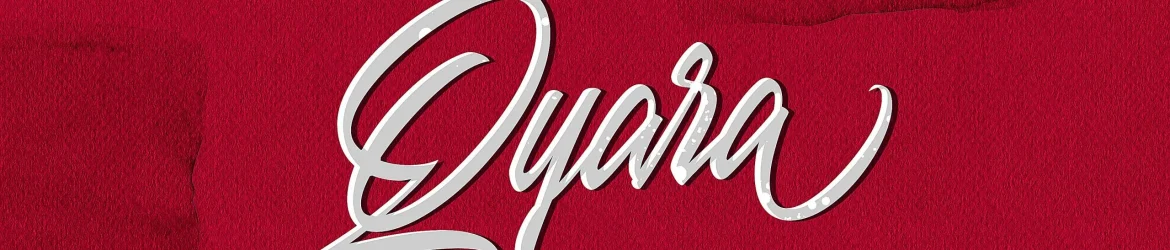
Qyara Calligraphy Font – Fonte Grátis
Qyara Calligraphy Font
Aqui está a descrição conforme solicitado: Na busca por uma fonte chamativa para projetos que requerem uma aparência natural e perfeita, Hamilton traz-nos Qyara Font. Uma fonte tipográfica de escrita cursiva cuidadosamente escrita com um estilo elegante, ideal para diversos tipos de design. Seja para criações como logotipos, produtos ou estilos de embalagem, essa fonte é perfeita e abrange uma completa coleção de letras maiúsculas e minúsculas, símbolos multilingue, números e pontuações. O que torna a Qyara Font ainda mais especial são os ligadores que adicionam um toque de naturalidade às suas criações. É perfeita para estilos como rótulos de embalagens, roupas de marca ou produtos digitais. Hamilton criou uma fonte à mão única e delicada, certificando-se de que cada letra traga vida a seus projetos. Qyara é a escolha certa para quem busca um design perfeito e natural em seu próximo projeto. Descubra o charme e a elegância da Qyara Font e explore o seu poder para transformar qualquer design.